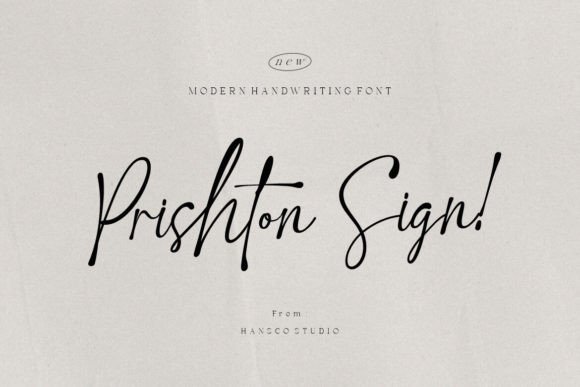
Prishton Sign
หากคุณกำลังมองหาเนื้อหาคุณภาพสูงเช่น Prishton Sign แพ็คเกจพรีเมียมนี้เป็นตัวเลือกที่ยอดเยี่ยมสำหรับโปรเจ็กต์สร้างสรรค์ของคุณ
สร้างขึ้นอย่างแม่นยำ Prishton Sign ให้เวกเตอร์ที่สะอาด พิมพ์ตัวอักษรที่ราบรื่น และใบอนุญาตเชิงพาณิชย์เพื่อความสบายใจ
ไม่ว่าคุณจะสร้างผลิตภัณฑ์ POD (Print on Demand) คำเชิญงานแต่งงาน หรือกราฟิกโซเชียลมีเดีย Prishton Sign ก็เหมาะสมอย่างยิ่ง